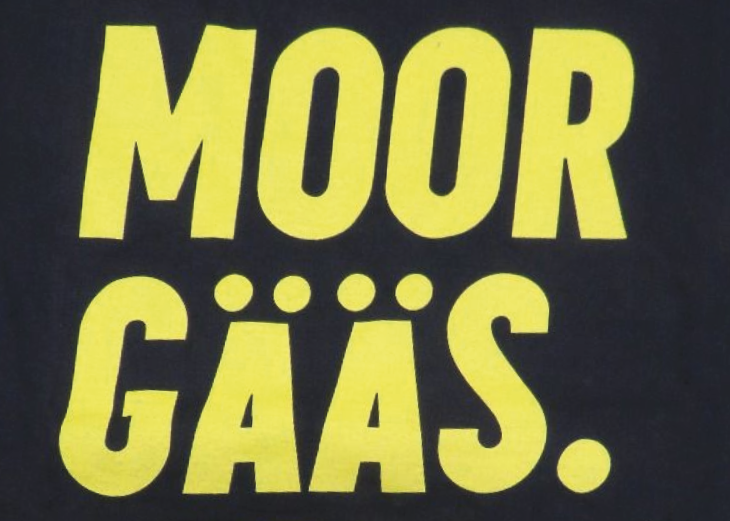
Schrift-Identifikation - Klassische Grotesk oder individueller Entwurf? (Moor gääs. Nou breiks)
Hallo zusammen, ich suche - mittlerweile recht verzweifelt - diese Schrift. Anfangs dachte ich "ganz einfach", mittlerweile sehe ich wahrscheinlich den Wald vor lauter Bäumen nicht. Ja, es kann sein, daß Teile "modifiziert" sind (beispielsweise das "Ä", vielleicht auch das leicht kursive), aber die Basis-Schrift ist doch eine ganz... einfache... bekannte. Nein?
p.s.: Das Bild stammt von einem T-Shirt, daher die "Wellen" in den Buchstaben "M" und im "G". Im Original sind die Buchstaben "sauber".
Spontan erinnert mich die Schrift an die Kapra Neue. Da passt allerdings das S nicht. Das kommt mir wiederum sehr bekannt vor ... vielleicht komm ich noch drauf.